Bạn có biết rằng một typeface độc đáo có thể giúp thương hiệu của bạn tăng trưởng về mặt nhận diện “kinh khủng” như thế nào không? Bài viết này sẽ giúp bạn hiểu rõ hơn về vai trò của typeface, cách lựa chọn typeface phù hợp và những lợi ích mà typeface mang lại. Từ đó, bạn sẽ hiểu hơn về cách tạo ra một thương hiệu độc đáo và ấn tượng chỉ bằng việc lựa chọn một typeface phù hợp.
Có thể nói rằng brand typeface còn có ý nghĩa nhiều hơn cả một phông chữ, hay trịnh trọng hơn, typeface còn được xem là trái tim của một thương hiệu. Trong vô vàn lựa chọn phông chữ, làm thế nào để bạn có thể chọn được một typeface vừa thể hiện được cá tính riêng biệt của doanh nghiệp, vừa tạo nên sự khác biệt so với hàng ngàn đối thủ cạnh tranh?
Để hiểu rõ hơn về tầm quan trọng của typeface, chúng ta cần nhận ra rằng phông chữ không chỉ đơn thuần là những ký tự. Chúng còn mang trong mình một sức mạnh vô hình, có khả năng truyền tải cảm xúc và thông điệp một cách sâu sắc. Khi kết hợp hài hòa với một thương hiệu, typeface sẽ giúp củng cố bản sắc và tạo nên dấu ấn riêng biệt, giúp doanh nghiệp trở nên nổi bật giữa hàng ngàn đối thủ cạnh tranh.
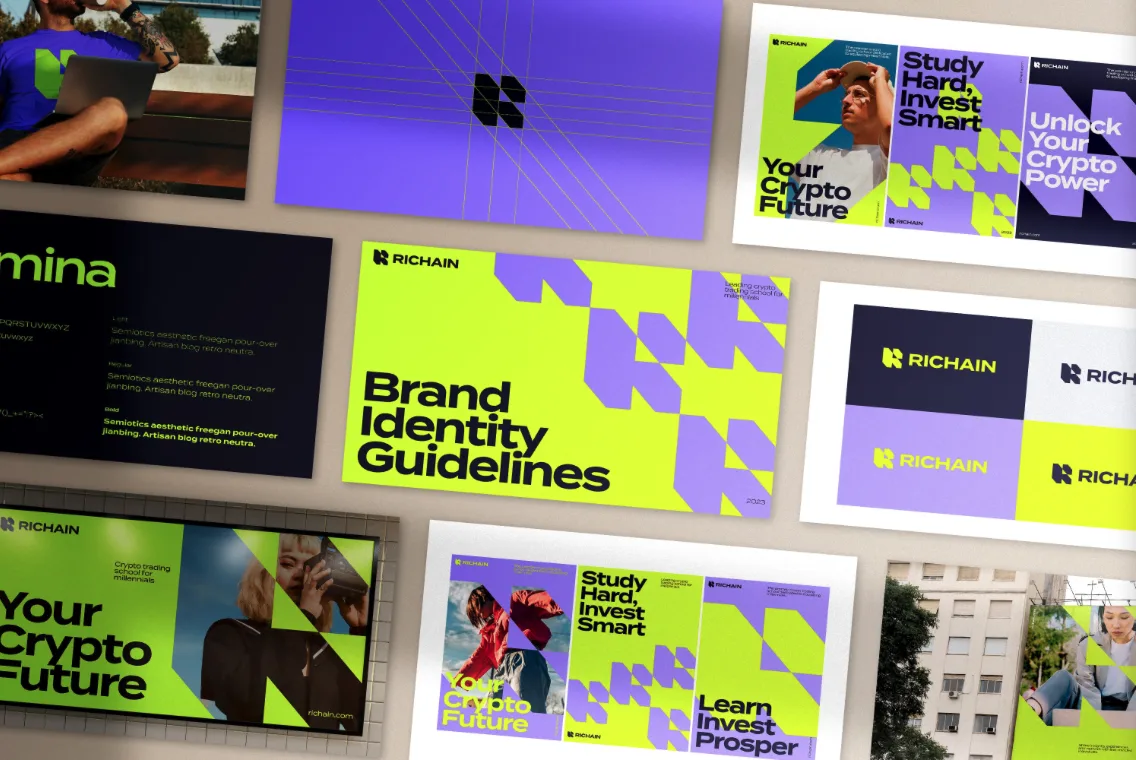
Typeface thương hiệu là gì?
Typeface thương hiệu là một yếu tố cốt lõi trong hệ thống nhận diện thương hiệu của mọi doanh nghiệp. Đó chính là bộ mặt chữ viết đặc trưng, được lựa chọn kỹ lưỡng và sử dụng thống nhất trong tất cả các tài liệu, ấn phẩm và giao tiếp của thương hiệu. Nói một cách đơn giản, typeface thương hiệu là “chữ ký” độc đáo của một thương hiệu, giúp người tiêu dùng dễ dàng nhận diện và ghi nhớ.
Cũng giống như logo hay bảng màu, typeface thương hiệu được quy định rõ ràng trong hướng dẫn nhận diện thương hiệu (brand guideline). Tài liệu này sẽ cung cấp các thông tin chi tiết về cách sử dụng typeface, bao gồm các biến thể, kích thước, màu sắc, khoảng cách giữa các chữ cái, và cả những trường hợp ngoại lệ.
Để sở hữu một typeface thương hiệu, doanh nghiệp có hai lựa chọn chính. Đầu tiên, bạn có thể thiết kế tùy chỉnh một typeface hoàn toàn riêng biệt, phản ánh rõ nét cá tính và giá trị của thương hiệu. Tuy nhiên, đây là một quá trình đòi hỏi nhiều thời gian và chi phí. Thay vào đó, bạn có thể tải xuống từ các kho typeface trên mạng với đa dạng phong cách. Với phương án này, bạn sẽ dễ dàng tìm kiếm và lựa chọn một typeface phù hợp mà không tốn quá nhiều công sức.
Brand typeface vs. brand typography vs. brand font vs. logo font
Khi nói đến thiết kế thương hiệu, việc hiểu rõ các thuật ngữ liên quan đến chữ viết là vô cùng quan trọng. Ba thuật ngữ thường được sử dụng là typography, typeface và font. Mặc dù chúng có vẻ giống nhau, nhưng mỗi thuật ngữ lại mang một ý nghĩa khác nhau.
- Typography (thiết kế chữ) là nghệ thuật sắp xếp và trình bày văn bản một cách thẩm mỹ. Nó bao gồm các yếu tố như: cách căn lề, khoảng cách giữa các chữ cái (kerning), khoảng cách giữa các dòng (leading), và kiểu chữ (font). Typography tạo nên sự hài hòa và cân đối cho thiết kế, giúp truyền tải thông điệp một cách hiệu quả.
- Typeface (kiểu chữ) là mẫu thiết kế cụ thể của các chữ cái, số và ký hiệu. Ví dụ, Helvetica, Times New Roman, Arial là những kiểu chữ phổ biến. Mỗi kiểu chữ có một phong cách riêng, từ hiện đại, trẻ trung đến cổ điển, sang trọng.
- Font (phông chữ) là tập tin kỹ thuật số chứa thông tin về một kiểu chữ. Nói cách khác, font là phiên bản kỹ thuật số của typeface, cho phép chúng ta sử dụng kiểu chữ đó trên máy tính.
Typeface thương hiệu là một kiểu chữ đặc biệt, được lựa chọn và sử dụng xuyên suốt trong tất cả các tài liệu của một thương hiệu. Nó đóng vai trò như một “bộ mặt” của thương hiệu, giúp tạo nên sự nhận diện và thống nhất. Coca-Cola là một ví dụ điển hình về việc sử dụng typeface để xây dựng thương hiệu. Logo của Coca-Cola với phông chữ đặc trưng đã trở thành một biểu tượng toàn cầu, được nhận biết ngay cả khi người ta chỉ nhìn thấy một phần nhỏ.
Font logo có thể xem như một biến thể đặc biệt của typeface thương hiệu. Nó kế thừa những đặc điểm cơ bản của typeface thương hiệu về phong cách và tính nhất quán, nhưng được điều chỉnh để phù hợp với yêu cầu cụ thể của thiết kế logo. Trong nhiều trường hợp, font logo có thể được thiết kế riêng để tạo nên một dấu ấn độc đáo, góp phần xây dựng một hệ thống nhận diện thương hiệu hoàn chỉnh.
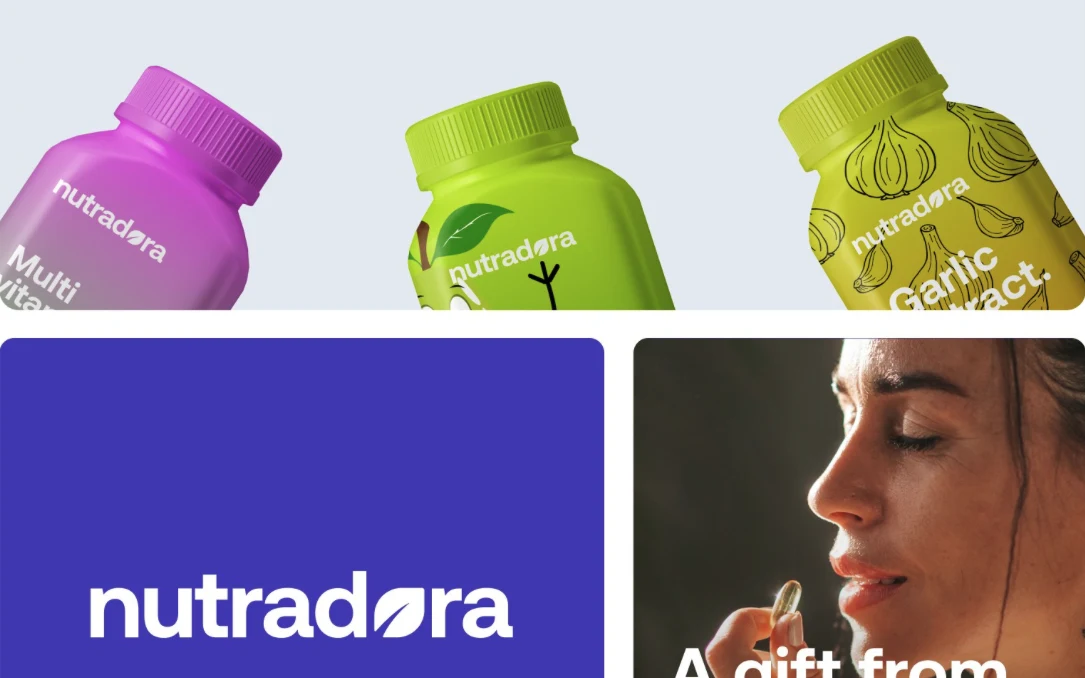
Typeface thương hiệu thường sẽ được sử dụng ở đâu?
Brand typeface là yếu tố quan trọng góp phần tạo nên diện mạo và cá tính riêng biệt cho thương hiệu. Chúng ta có thể bắt gặp kiểu chữ thương hiệu ở khắp mọi nơi trong cuộc sống hàng ngày, từ những ấn phẩm truyền thống đến các nền tảng kỹ thuật số.
Các ứng dụng phổ biến của brand typeface:
- Truyền thông in ấn: Danh thiếp, tờ rơi, brochure, báo cáo, bao bì sản phẩm,…
- Truyền thông trực tuyến: Website, blog, mạng xã hội, email marketing, quảng cáo trực tuyến,…
- Môi trường xung quanh: Biển hiệu, bảng quảng cáo, poster,…
Tại sao typeface thương hiệu lại đóng nhiều vai trò quan trọng khác nhau? Bởi vì mỗi phần tử trong thiết kế đồ họa đều có một mục đích cụ thể. Kiểu chữ cũng vậy, chúng ta cần sử dụng những kiểu chữ khác nhau để truyền đạt những thông điệp khác nhau. Ví dụ:
- Tiêu đề: Cần sử dụng kiểu chữ nổi bật, thu hút sự chú ý để làm nổi bật thông tin chính.
- Văn bản chính: Nên sử dụng kiểu chữ dễ đọc, thoải mái cho mắt để người đọc dễ dàng tiếp thu nội dung.
- CTA (Call to Action): Cần sử dụng kiểu chữ tạo sự nhấn mạnh, khuyến khích người dùng thực hiện hành động mong muốn.
- Chú thích, phụ đề: Có thể sử dụng kiểu chữ nhỏ hơn, ít nổi bật hơn so với văn bản chính.
Bên cạnh đó, bạn cũng cần nắm các yếu tố tạo nên sự đa dạng của kiểu chữ thương hiệu như:
- Độ đậm nhạt: Từ chữ thường đến chữ đậm, mỗi cấp độ đậm nhạt sẽ tạo ra cảm giác khác nhau.
- Kích thước: Kích thước chữ ảnh hưởng đến sự chú ý của người đọc.
- Kiểu chữ: Có rất nhiều kiểu chữ khác nhau, từ serif (có chân) đến sans-serif (không chân), mỗi kiểu chữ đều mang một phong cách riêng.
- Chữ nghiêng: Chữ nghiêng tạo cảm giác mềm mại, uyển chuyển hơn.
- Khoảng cách giữa các chữ cái: Khoảng cách giữa các chữ cái ảnh hưởng đến độ thoáng và sự cân đối của dòng chữ.
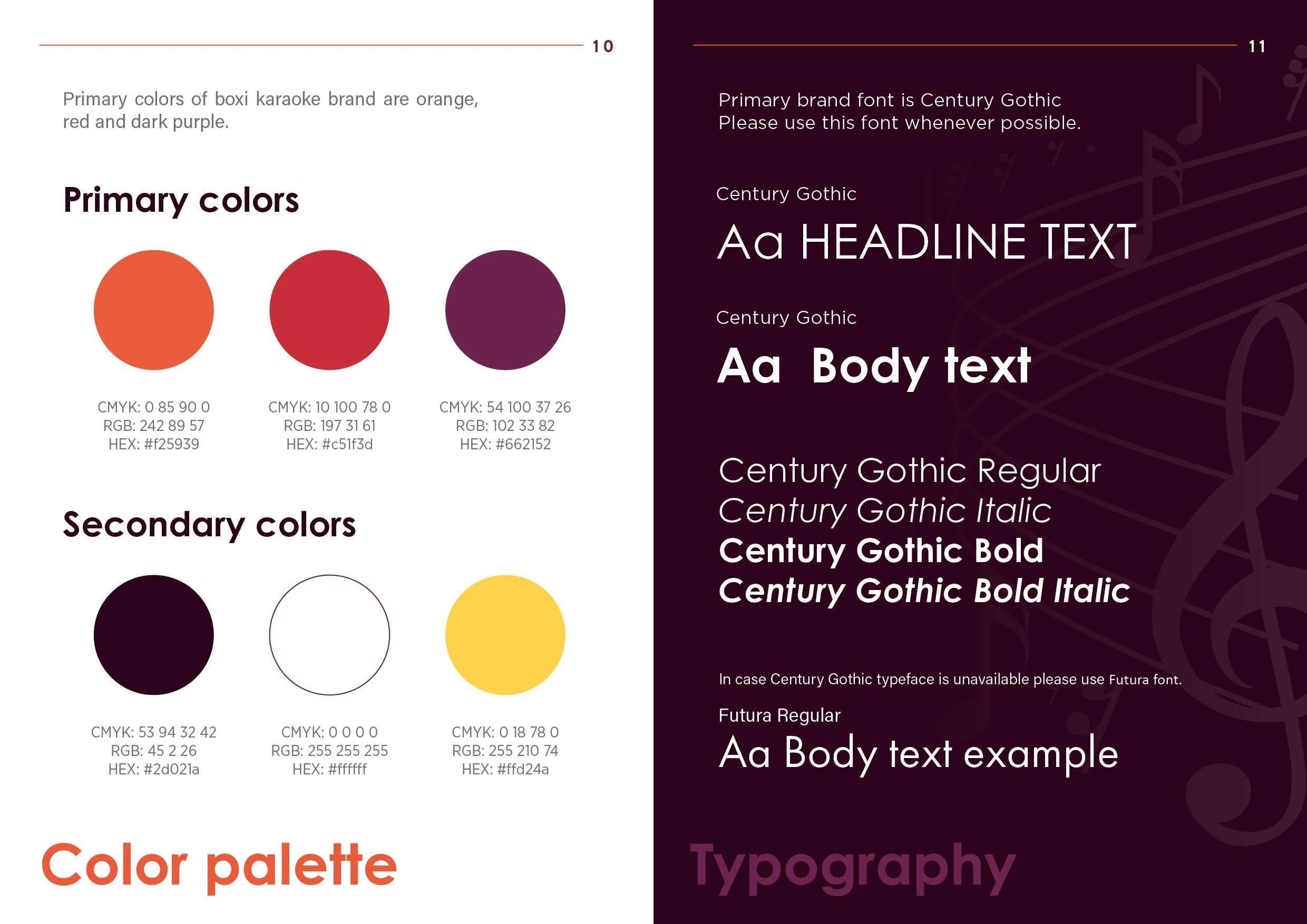
Nguồn ảnh: Vista Print
Tại sao kiểu chữ thương hiệu (brand typeface) lại quan trọng đến vậy?
Kiểu chữ thương hiệu không chỉ đơn thuần là những chữ cái, số và ký hiệu. Nó là một công cụ thiết kế chiến lược, đóng vai trò quan trọng trong việc xây dựng và truyền tải bản sắc thương hiệu. Kiểu chữ vừa là một phương tiện giao tiếp trực quan, giúp thể hiện tính cách, giá trị và phong cách của thương hiệu, vừa là một yếu tố tạo nên sự nhất quán trong toàn bộ hệ thống nhận diện thương hiệu. Ví dụ, một kiểu chữ đậm, góc cạnh sẽ tạo cảm giác mạnh mẽ, năng động, phù hợp với các thương hiệu công nghệ, trong khi một kiểu chữ mềm mại, tròn trịa lại gợi lên sự thân thiện, gần gũi, thích hợp cho các thương hiệu thời trang.
Việc lựa chọn và sử dụng kiểu chữ một cách phù hợp mang lại nhiều lợi ích cho thương hiệu. Đầu tiên, typeface giúp khách hàng dễ dàng nhận diện thương hiệu của bạn giữa vô vàn thương hiệu khác trên thị trường. Thứ hai, mỗi typeface đều mang một ý nghĩa và cảm xúc riêng, việc lựa chọn typeface phù hợp sẽ giúp bạn truyền đạt thông điệp một cách chính xác và hiệu quả đến đối tượng khách hàng mục tiêu. Bên cạnh đó, một thương hiệu có thiết kế chuyên nghiệp, trong đó có việc sử dụng typeface một cách thống nhất, sẽ tạo cảm giác tin cậy và uy tín cho khách hàng, giúp tăng cường lòng trung thành của khách hàng. Cuối cùng, typeface cũng đóng vai trò quan trọng trong việc giúp thương hiệu của bạn nổi bật và khác biệt so với các đối thủ cạnh tranh khác.
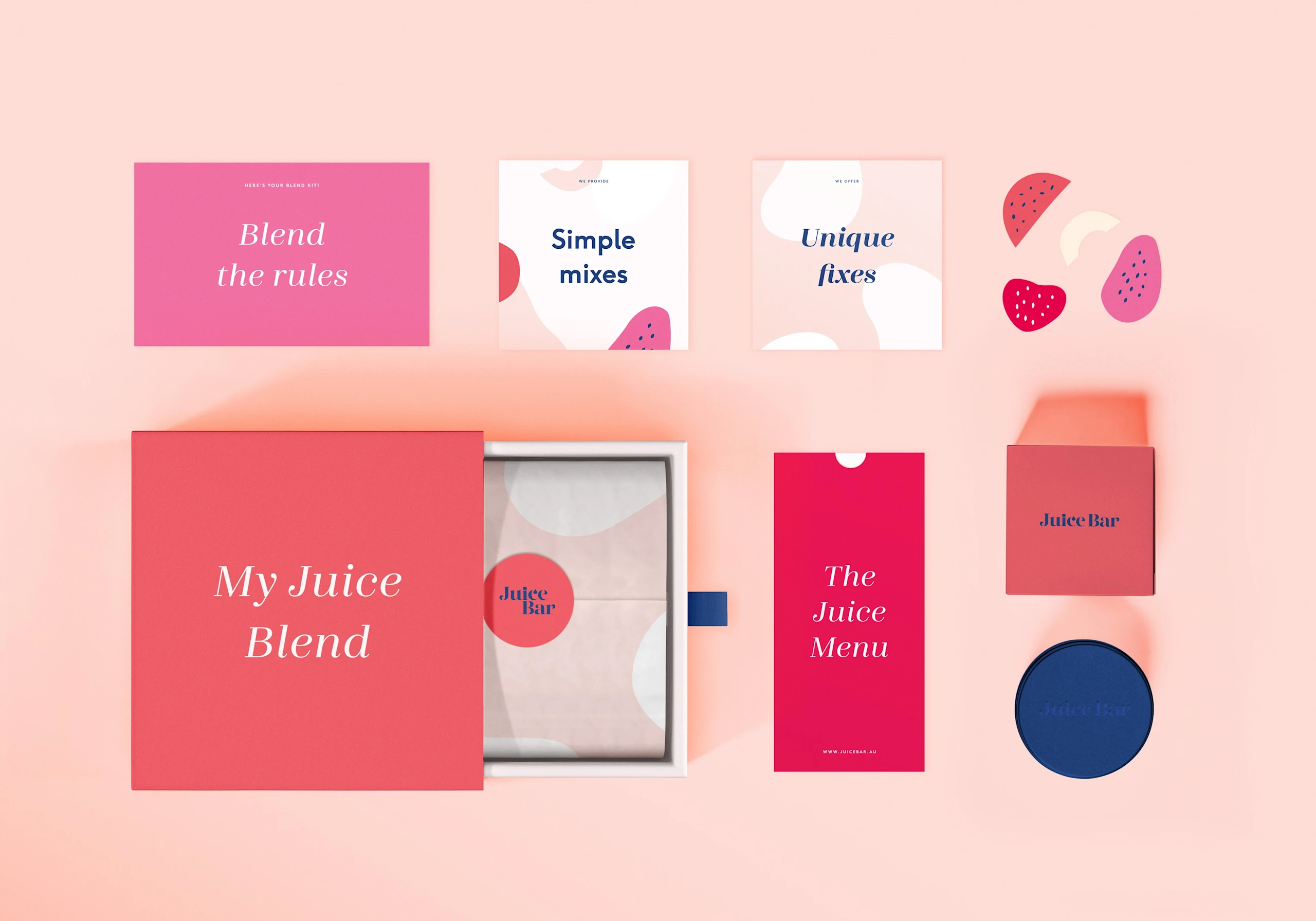
Nguồn ảnh: Vista Print
4 bước đơn giản giúp bạn chọn một brand typeface phù hợp nhất
Bước 1: Đặt nền móng vững chắc cho thương hiệu của bạn
Trước khi bắt đầu lựa chọn typeface cho thương hiệu, việc đầu tiên bạn cần làm là xây dựng một bản sắc thương hiệu rõ ràng. Hãy hình dung thương hiệu của bạn như một cá nhân với những đặc điểm riêng biệt. Để làm được điều này, bạn cần tạo một tài liệu tổng quan, bao gồm sứ mệnh, tầm nhìn, giá trị cốt lõi, giọng điệu giao tiếp và tính cách thương hiệu. Điều này sẽ giúp bạn hình dung rõ hơn về hình ảnh mà bạn muốn xây dựng. Bên cạnh đó, việc hiểu rõ đối tượng khách hàng mục tiêu, những gì họ quan tâm và thích thú cũng rất quan trọng. Việc phân tích đối tượng khách hàng sẽ giúp bạn lựa chọn typeface phù hợp với thị hiếu và sở thích của họ. Cuối cùng, đừng quên nghiên cứu cách các đối thủ cạnh tranh sử dụng typeface. Điều đó không chỉ giúp bạn học hỏi những điểm mạnh của họ mà còn giúp bạn tìm ra những điểm khác biệt để tạo nên dấu ấn riêng cho thương hiệu của mình.
Dưới đây là một số câu hỏi mà bạn có thể tự hỏi để xác định bản sắc thương hiệu:
- Thương hiệu của bạn đại diện cho điều gì?
- Bạn muốn khách hàng cảm nhận như thế nào về thương hiệu của bạn?
- Ai là đối tượng khách hàng mục tiêu của bạn?
- Phong cách thiết kế tổng thể của thương hiệu bạn là gì?
- Các đối thủ cạnh tranh của bạn đang sử dụng kiểu chữ nào?
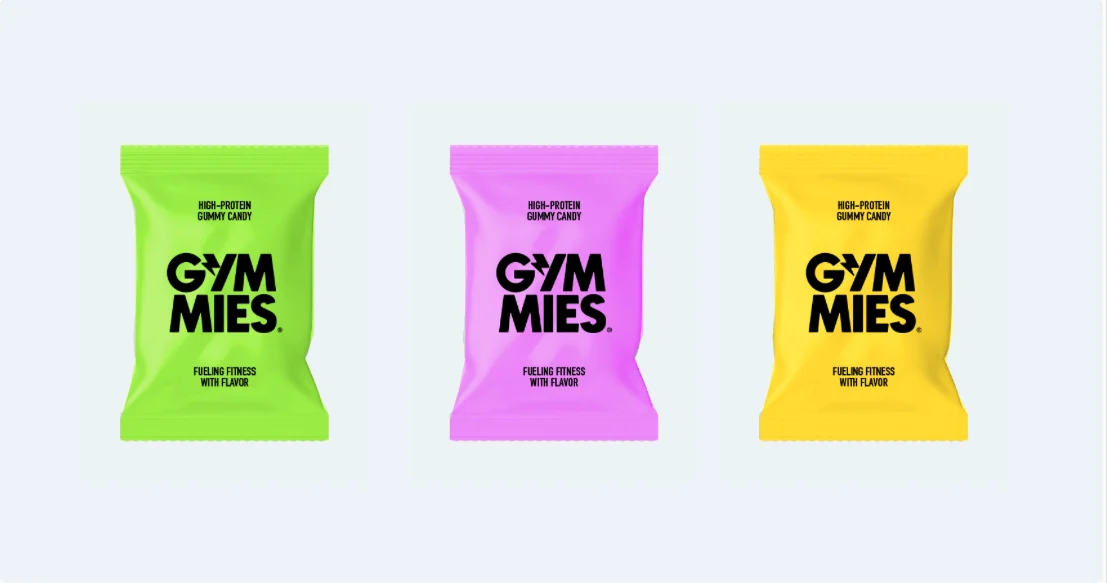
Nguồn ảnh: Vista Print
Vì sao bước này lại vô cùng quan trọng?
Việc xác định rõ bản sắc thương hiệu là vô cùng quan trọng trong quá trình lựa chọn typeface. Một bản sắc thương hiệu rõ ràng sẽ giúp bạn đưa ra những quyết định đúng đắn và tránh được những sai lầm không đáng có. Khi bạn hiểu rõ thương hiệu của mình đại diện cho điều gì, bạn muốn khách hàng cảm nhận như thế nào về thương hiệu, và ai là đối tượng khách hàng mục tiêu, bạn sẽ dễ dàng lựa chọn được typeface phù hợp. Bởi vì kiểu chữ không chỉ là một yếu tố thiết kế đơn thuần mà còn đóng vai trò quan trọng trong việc truyền tải thông điệp và hình ảnh của thương hiệu. Một typeface phù hợp sẽ giúp bạn tạo nên sự nhất quán trong tất cả các tài liệu và ấn phẩm của thương hiệu, từ đó xây dựng một hình ảnh chuyên nghiệp và đáng tin cậy trong mắt khách hàng.
Bước 2: Tìm hiểu ngôn ngữ của thiết kế: Tính cách ẩn sau từng kiểu chữ
Việc lựa chọn một typeface không chỉ đơn thuần là chọn một bộ ký tự đẹp mắt. Mỗi kiểu chữ mang trong mình một câu chuyện, một tính cách riêng biệt, và có khả năng truyền tải những thông điệp sâu sắc về thương hiệu của bạn. Hãy hình dung typeface như một chiếc áo quần, nó phản ánh phong cách và cá tính của người mặc.
“Tính cách” của một typeface được thể hiện qua nhiều yếu tố khác nhau. Đầu tiên, các thuộc tính hình thức như độ đậm nhạt, độ rộng hẹp của các ký tự, hình dạng của các đường nét, và sự có mặt của các yếu tố trang trí tạo nên một “ngôn ngữ hình ảnh” riêng biệt cho từng typeface. Bên cạnh đó, nhiều typeface còn mang trong mình những giá trị văn hóa và lịch sử nhất định, tạo nên những liên tưởng sâu sắc. Ví dụ, các kiểu chữ serif thường gợi nhớ đến truyền thống và sự sang trọng, trong khi các kiểu chữ sans serif lại mang đến cảm giác hiện đại và đơn giản. Cuối cùng, không thể không nhắc đến khả năng gợi cảm xúc và tâm lý của typeface. Một typeface tròn trịa, mềm mại có thể tạo cảm giác thân thiện và gần gũi, trong khi một typeface góc cạnh, mạnh mẽ lại truyền tải cảm giác quyền lực và năng động.
Dưới đây là các loại kiểu chữ phổ biến và ý nghĩa của chúng:
- Serif: Với những đường nét có chân, kiểu chữ serif thường được sử dụng trong các ấn phẩm truyền thống như sách, báo. Chúng tạo cảm giác cổ điển, đáng tin cậy và chuyên nghiệp.
- Sans serif: Không có các đường nét chân, kiểu chữ sans serif mang đến cảm giác hiện đại, sạch sẽ và dễ đọc. Chúng thường được sử dụng trong thiết kế giao diện, quảng cáo và các ấn phẩm hướng đến đối tượng trẻ.
- Script: Nhắc nhớ đến nét chữ viết tay, kiểu chữ script mang đến cảm giác mềm mại, uyển chuyển và lãng mạn. Chúng thường được sử dụng trong các thiết kế mang tính cá nhân và sáng tạo.
- Display: Với những thiết kế mang tính khác biệt, kiểu chữ display thường được sử dụng để tạo điểm nhấn cho tiêu đề, logo hoặc các yếu tố đồ họa khác.
Bước 3: Hiểu rõ về chi phí
Việc lựa chọn kiểu chữ cho thương hiệu không chỉ dựa trên yếu tố thẩm mỹ mà còn cần cân nhắc kỹ lưỡng đến vấn đề chi phí. Chi phí sử dụng một typeface phụ thuộc vào nhiều yếu tố khác nhau, bao gồm loại giấy phép và mục đích sử dụng.
Phông chữ miễn phí
Phông chữ miễn phí là một lựa chọn phổ biến cho nhiều người dùng. Chúng ta có thể dễ dàng tìm thấy các phông chữ này trên hầu hết các hệ điều hành, ví dụ như Times New Roman hay Arial. Những phông chữ hệ thống này thường được sử dụng miễn phí cho cả mục đích cá nhân và thương mại. Ngoài ra, còn có một nguồn phông chữ miễn phí phong phú khác đến từ cộng đồng mã nguồn mở. Google Fonts là một ví dụ điển hình, cung cấp hàng nghìn kiểu chữ đa dạng và được cập nhật thường xuyên. Các phông chữ mã nguồn mở thường đi kèm với những điều khoản sử dụng cụ thể, cho phép người dùng tự do sử dụng, chỉnh sửa và thậm chí phân phối lại với một số điều kiện nhất định.
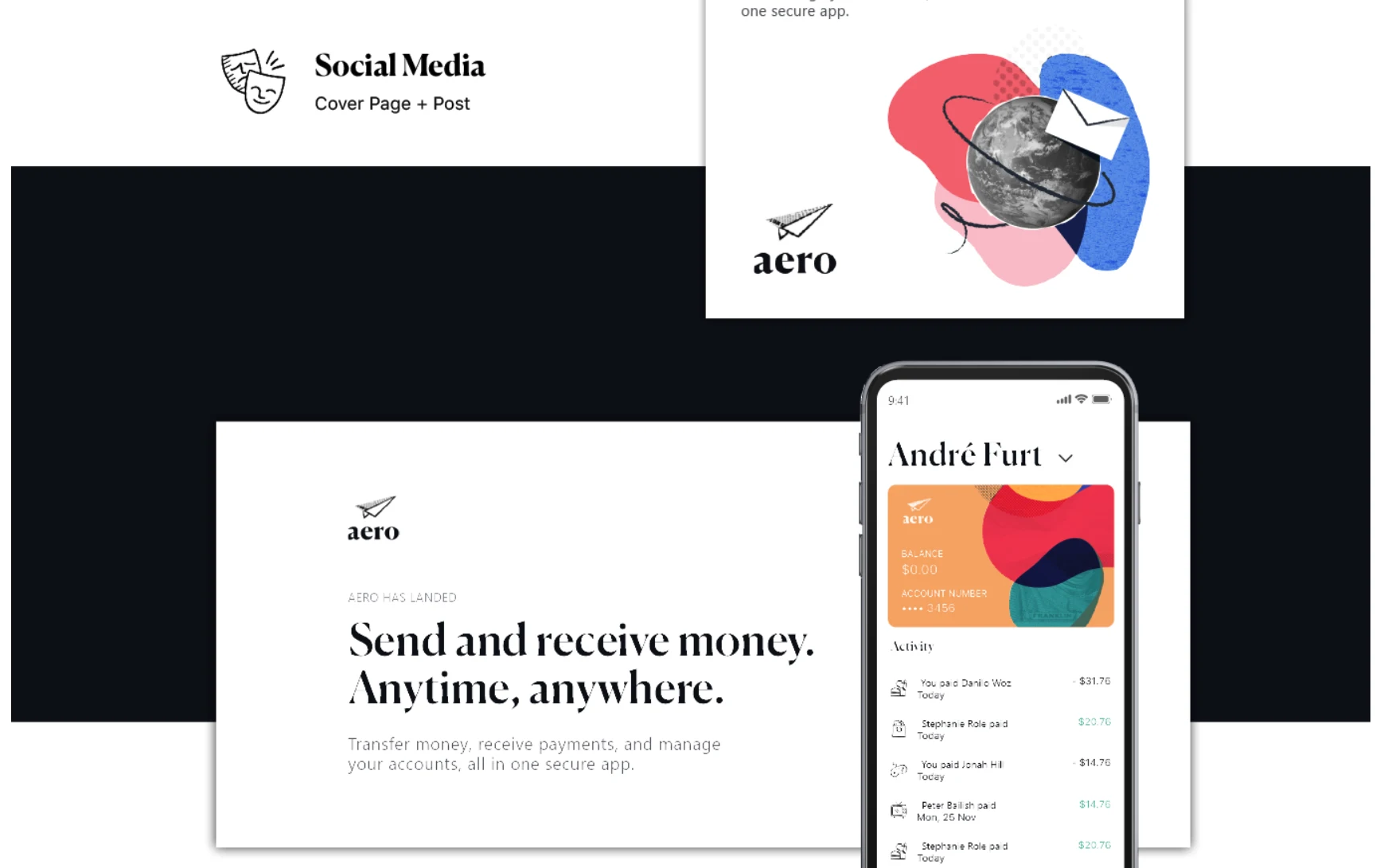
Nguồn ảnh: Vista Print
Phông chữ thương mại
Phông chữ thương mại, những sản phẩm độc đáo được tạo ra bởi các nhà thiết kế chuyên nghiệp, thường yêu cầu bạn phải mua giấy phép sử dụng. Chi phí cho một giấy phép phông chữ có thể dao động khá lớn, phụ thuộc vào nhiều yếu tố. Trước hết, loại giấy phép bạn chọn sẽ ảnh hưởng trực tiếp đến chi phí. Bạn có thể lựa chọn mua giấy phép sử dụng một lần để sở hữu phông chữ mãi mãi, hoặc mua giấy phép định kỳ nếu nhu cầu sử dụng của bạn thay đổi theo thời gian. Ngoài ra, còn có loại giấy phép theo dự án, phù hợp cho những dự án nhỏ lẻ.
Tiếp theo, quy mô sử dụng cũng là một yếu tố quan trọng. Số lượng thiết bị, số lượng người dùng, và mục đích sử dụng (in ấn, web,…) sẽ ảnh hưởng trực tiếp đến giá cả của giấy phép. Các dự án lớn, sử dụng phông chữ với số lượng lớn thường yêu cầu những giấy phép đặc biệt và chi phí cao hơn. Cuối cùng, nhà cung cấp và độ phổ biến của phông chữ cũng là những yếu tố cần cân nhắc. Những phông chữ nổi tiếng, được nhiều người sử dụng thường có giá cao hơn so với những phông chữ ít phổ biến. Tóm lại, việc sử dụng phông chữ thương mại đòi hỏi bạn phải đầu tư một khoản chi phí nhất định. Tuy nhiên, đổi lại, bạn sẽ sở hữu những kiểu chữ độc đáo, chất lượng cao và phù hợp với nhu cầu sử dụng của mình.
So sánh chung giữa phông chữ miễn phí và phông chữ thương mại
| Tính năng | Phông chữ miễn phí | Phông chữ thương mại |
| Nguồn gốc | Cài đặt sẵn trên hệ thống, phát triển mã nguồn mở | Được tạo bởi các nhà thiết kế chuyên nghiệp |
| Độ phổ biến | Rất phổ biến, dễ tìm | Ít phổ biến hơn, cần tìm kiếm kỹ |
| Tính độc đáo | Ít độc đáo, nhiều người sử dụng | Độc đáo, ít người sử dụng |
| Chi phí | Miễn phí | Có phí |
| Quyền sử dụng | Hạn chế về mục đích sử dụng | Linh hoạt hơn |
| Chất lượng | Khá ổn định | Chất lượng cao, thiết kế chuyên nghiệp |
Khi sử dụng phông chữ, đặc biệt là phông chữ thương mại, bạn cần lưu ý một số điều quan trọng để tránh vi phạm bản quyền và đảm bảo thiết kế của mình đạt hiệu quả cao nhất. Trước hết, hãy luôn đọc kỹ điều khoản sử dụng của từng phông chữ. Điều khoản này sẽ cung cấp thông tin chi tiết về quyền hạn và hạn chế khi sử dụng phông chữ đó, giúp bạn tránh những rắc rối pháp lý không đáng có.
Thứ hai, việc lựa chọn phông chữ phù hợp là rất quan trọng. Hãy chọn những phông chữ phù hợp với mục đích sử dụng, đối tượng khách hàng và phong cách thiết kế chung. Để tạo ra những thiết kế đa dạng và hấp dẫn, bạn có thể kết hợp cả phông chữ miễn phí và phông chữ thương mại. Tuy nhiên, hãy tìm kiếm các nguồn cung cấp phông chữ uy tín để đảm bảo chất lượng và tránh tải về những phông chữ có vấn đề về bản quyền.
Nếu bạn chưa tự tin về kiến thức chuyên sâu về typography, hãy cân nhắc nhờ đến sự trợ giúp của các nhà thiết kế chuyên nghiệp. Với kiến thức chuyên môn sâu rộng, kinh nghiệm thực tế và khả năng tư vấn, các nhà thiết kế sẽ giúp bạn lựa chọn được phông chữ phù hợp nhất, tối ưu hóa thiết kế và tiết kiệm thời gian. Thay vì mất nhiều thời gian để tự mình tìm hiểu và lựa chọn, bạn có thể tập trung vào các công việc khác, trong khi nhà thiết kế sẽ đảm bảo rằng phông chữ được lựa chọn sẽ phù hợp với thương hiệu của bạn, tạo ra ấn tượng tốt với khách hàng và mang lại hiệu quả cao trong truyền thông.
Bước 4: Thử nghiệm với các typeface khác nhau
Trước khi quyết định kiểu chữ thương hiệu cuối cùng, việc kiểm nghiệm thực tế là vô cùng quan trọng. Hãy thử nghiệm một số tùy chọn khác nhau với đối tượng mục tiêu để đánh giá hai yếu tố chính: cộng hưởng cảm xúc và tính thực tiễn. Kiểu chữ không chỉ cần đẹp mắt mà còn phải truyền tải được thông điệp và giá trị thương hiệu. Đồng thời, nó cần đảm bảo tính dễ đọc, dễ nhận biết, đặc biệt là khi sử dụng ở các kích thước khác nhau. Một cách đơn giản để kiểm tra tính dễ đọc là thử đọc một đoạn văn bản sử dụng kiểu chữ đó từ một khoảng cách nhất định.
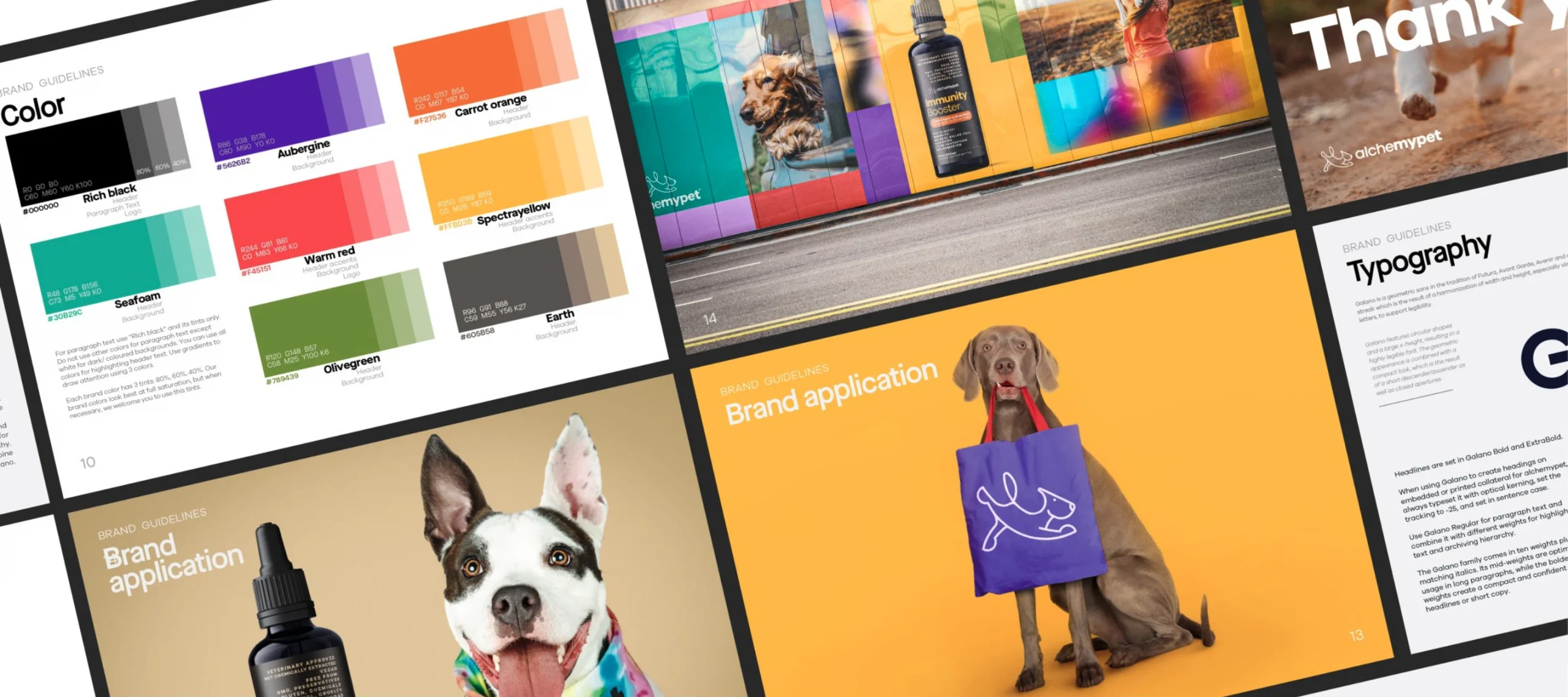
Nguồn ảnh: Vista Print
Để đánh giá hiệu quả của các kiểu chữ, chúng ta có thể áp dụng nhiều phương pháp kiểm nghiệm khác nhau. Trên nền tảng số, các trang web và mạng xã hội là những kênh lý tưởng để thử nghiệm. Bằng cách theo dõi các chỉ số như tỷ lệ nhấp chuột, lượt thích hay thời gian người dùng lưu trú trên trang, chúng ta có thể đánh giá sự tương tác và hiệu quả của kiểu chữ. Bên cạnh đó, các khảo sát trực tuyến cũng là những phương pháp hữu hiệu để thu thập ý kiến phản hồi trực tiếp từ người tiêu dùng về cảm nhận của họ đối với từng kiểu chữ.
Khi thử nghiệm các kiểu chữ, hãy nhớ tạo ra các mẫu thiết kế thực tế để đánh giá toàn diện hiệu quả của chúng trong ngữ cảnh sử dụng. Đừng chỉ đơn thuần hiển thị kiểu chữ một cách cô lập mà hãy đặt nó vào trong thiết kế hoàn chỉnh. Để có cái nhìn khách quan hơn, hãy so sánh kiểu chữ đang thử nghiệm với các tùy chọn khác. Ngoài ra, yếu tố văn hóa cũng rất quan trọng. Bởi vì mỗi kiểu chữ đều mang những ý nghĩa và cảm xúc khác nhau tùy thuộc vào nền văn hóa. Vì vậy, hãy đảm bảo rằng kiểu chữ bạn chọn phù hợp với đối tượng mục tiêu và văn hóa của họ.
Xu hướng phát triển của brand typeface
Xu hướng phát triển của brand typeface ngày càng đa dạng và sáng tạo hơn. Sự phát triển của công nghệ đã mở ra những cánh cửa mới cho thiết kế font chữ, cho phép các nhà thiết kế tạo ra những kiểu chữ độc đáo và cá tính hơn. Chúng ta đang chứng kiến sự kết hợp hài hòa giữa các yếu tố truyền thống và hiện đại, tạo nên những phong cách thiết kế font chữ mới lạ.
Bên cạnh đó, xu hướng tối giản cũng ngày càng được ưa chuộng, với những kiểu chữ tinh giản, rõ ràng và dễ đọc. Ngoài ra, sự quan tâm đến yếu tố con người và cảm xúc cũng được thể hiện rõ nét trong thiết kế font chữ, tạo ra những kiểu chữ mang đậm dấu ấn cá nhân và gần gũi với người dùng. Có thể nói, tương lai của brand typeface sẽ còn nhiều điều thú vị đang chờ đón, khi các nhà thiết kế không ngừng sáng tạo và khám phá những khả năng mới của typography.
Typeface thương hiệu tốt nhất nên là một typeface của riêng thương hiệu đó
Một typeface được thiết kế riêng sẽ giúp truyền tải chính xác thông điệp mà bạn muốn gửi gắm đến khách hàng, từ đó tạo dựng mối liên kết cảm xúc sâu sắc. Việc sở hữu một typeface thiết kế riêng cũng là cách để khẳng định đẳng cấp của thương hiệu. Nó cho thấy bạn là một thương hiệu đầu tư vào chất lượng và sự hoàn hảo. Tuy nhiên, việc lựa chọn một typeface phù hợp có thể là một quá trình phức tạp. Nếu bạn cần sự hỗ trợ, hãy tìm đến các nhà thiết kế chuyên nghiệp. Họ sẽ giúp bạn tạo ra một typeface độc đáo và phù hợp với thương hiệu của mình. Vì vậy, đừng ngần ngại đầu tư vào một typeface thiết kế. Nó chính là khoản đầu tư thông minh sẽ mang lại những lợi ích lâu dài cho thương hiệu của bạn.
Các yếu tố cần lưu ý khi thiết kế typeface thương hiệu
| Khả năng đọc | Đây là yếu tố quan trọng hàng đầu. Một typeface tốt phải đảm bảo dễ đọc, ngay cả khi được sử dụng trong các kích thước nhỏ hoặc trên các thiết bị khác nhau. |
| Tính nhất quán | Mỗi chữ cái trong một typeface phải có một phong cách thống nhất. Điều này bao gồm độ dày của nét, góc nghiêng, và các chi tiết nhỏ khác. Tính nhất quán giúp tạo nên một typeface hài hòa và chuyên nghiệp. |
| Tính độc đáo | Một typeface độc đáo sẽ giúp thương hiệu của bạn nổi bật. Tuy nhiên, sự độc đáo không có nghĩa là phải quá cầu kỳ hoặc khó đọc. Hãy tìm kiếm sự cân bằng giữa tính độc đáo và khả năng ứng dụng. |
| Tính linh hoạt | Một typeface tốt phải linh hoạt, có thể sử dụng được trong nhiều ngữ cảnh khác nhau, từ tiêu đề đến nội dung chính văn. Hãy đảm bảo typeface của bạn có đủ các biến thể (bold, italic,…) để đáp ứng các nhu cầu khác nhau. |
| Phù hợp với thương hiệu | Typeface cần phải phù hợp với hình ảnh và thông điệp của thương hiệu. Ví dụ, một thương hiệu công nghệ có thể chọn một typeface hiện đại và đơn giản, trong khi một thương hiệu thời trang cao cấp có thể chọn một typeface thanh lịch và tinh tế. |
| Khả năng mở rộng | Typeface cần phải hiển thị tốt ở các kích thước khác nhau, từ rất nhỏ đến rất lớn. Điều này đặc biệt quan trọng khi sử dụng typeface trên các thiết bị di động và màn hình có độ phân giải cao. |
| Tính ứng dụng | Typeface cần phải dễ sử dụng trong các phần mềm thiết kế đồ họa và các ứng dụng khác. Hãy đảm bảo typeface của bạn có đầy đủ các ký tự đặc biệt và hỗ trợ nhiều ngôn ngữ. |
| Khả năng truy cập | Một typeface tốt phải dễ đọc cho mọi người, bao gồm cả những người có thị lực kém. Hãy đảm bảo typeface của bạn có độ tương phản cao, khoảng cách giữa các dòng chữ hợp lý và không có các chi tiết quá nhỏ. |
Tạm kết
Chúng ta đã cùng nhau khám phá thế giới đa dạng của typeface và những tác động sâu sắc mà nó có thể mang lại cho thương hiệu. Tuy nhiên, việc thiết kế một typeface độc đáo không chỉ dừng lại ở kiến thức cơ bản. Đó là một hành trình sáng tạo, nơi bạn được tự do thể hiện cá tính và phong cách riêng. Hãy tiếp tục học hỏi, khám phá và đừng ngại thử nghiệm để tạo ra những typeface độc đáo, mang đậm dấu ấn cá nhân của bạn nhé!